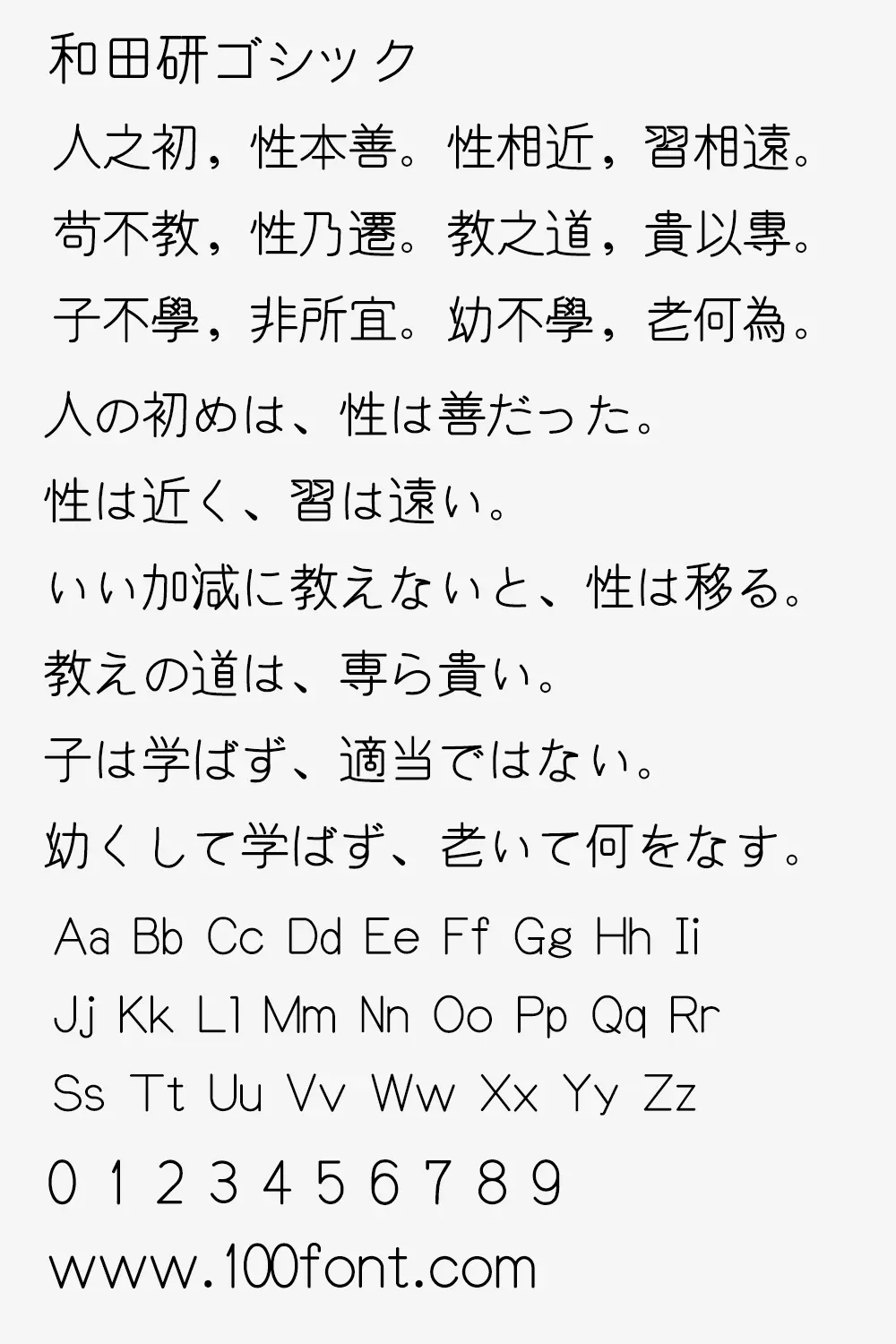
和田研ゴシック(和田研細丸ゴシック)是一款來之日本的細圓風格字體,作者是和田研,首次發佈於2004年,雖然是一款比較老的字體,但作者目前還在更新維護,和田研以簡單的元素來表達字體的美感,字體的直角轉折處都以橢圓角來做替代,整個字體充滿了濃濃的古典風格。(和田研細丸表示筆畫較細,和田研中丸表示筆畫較粗)